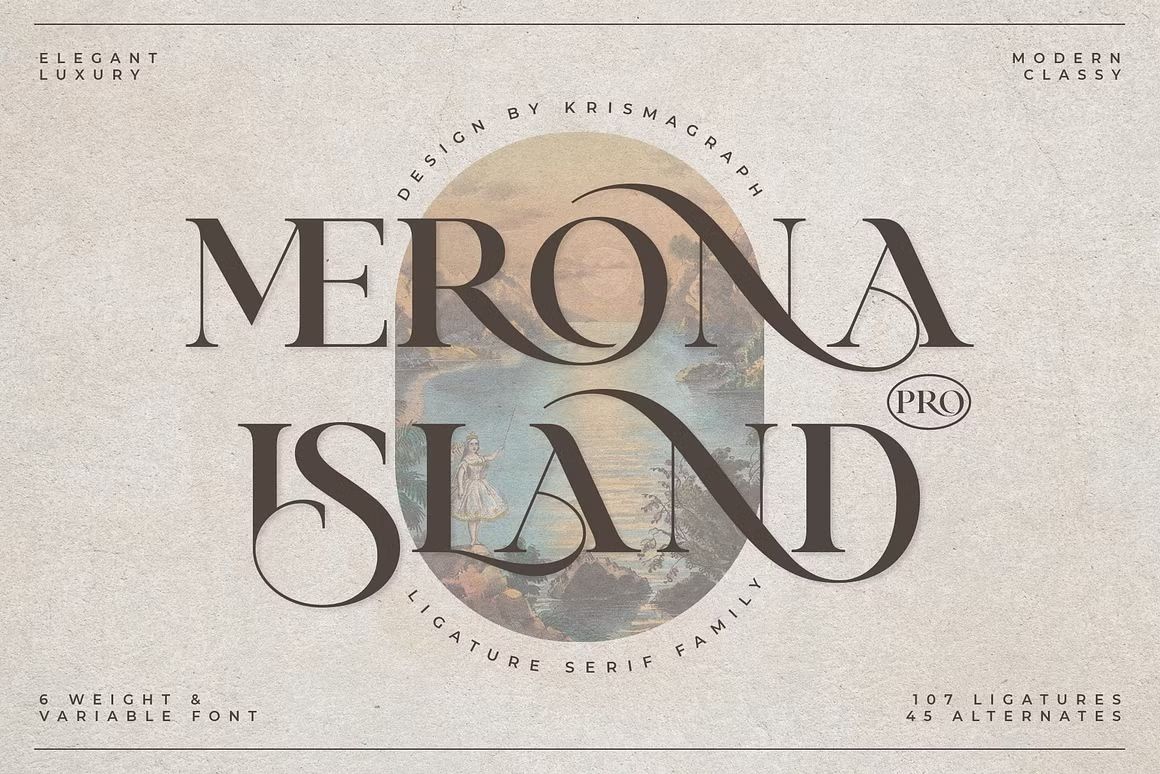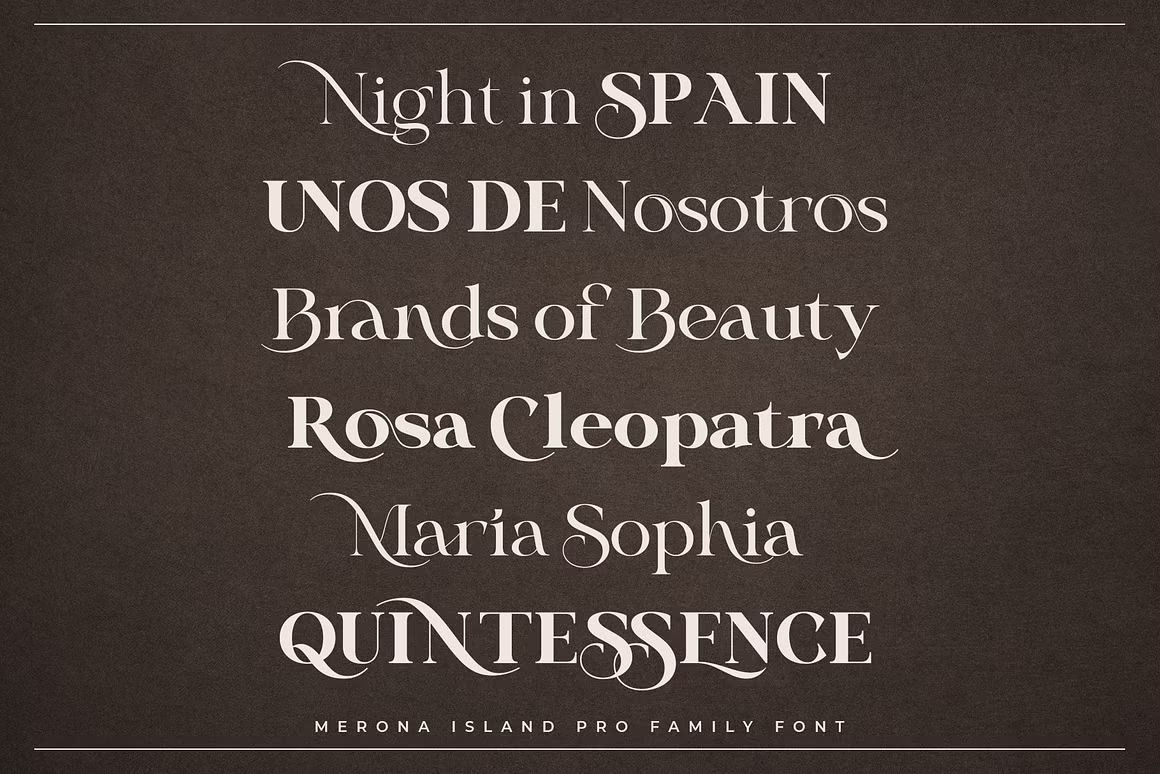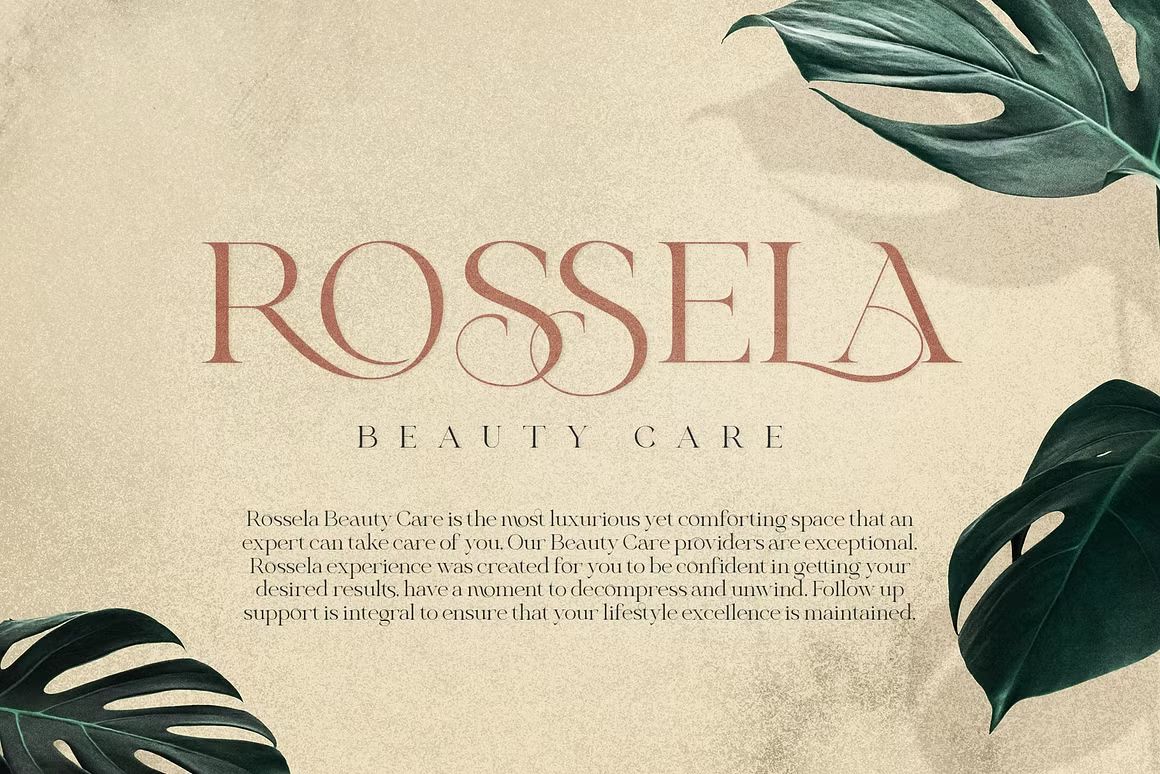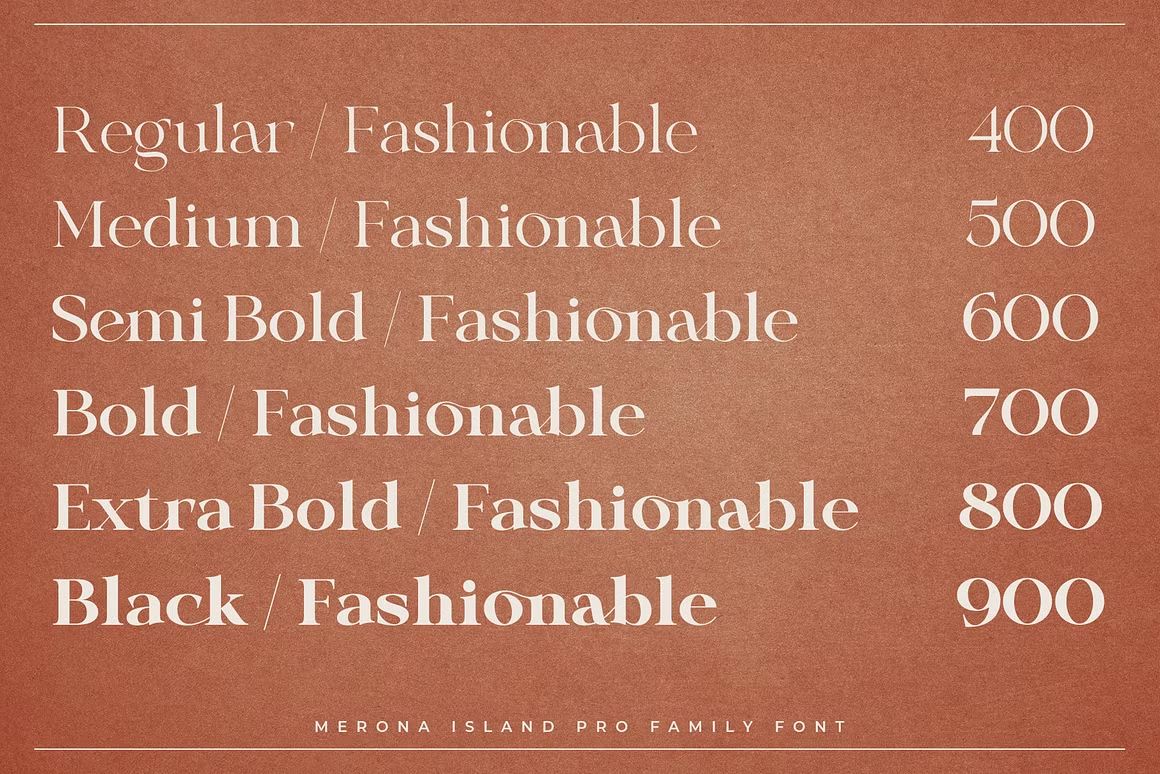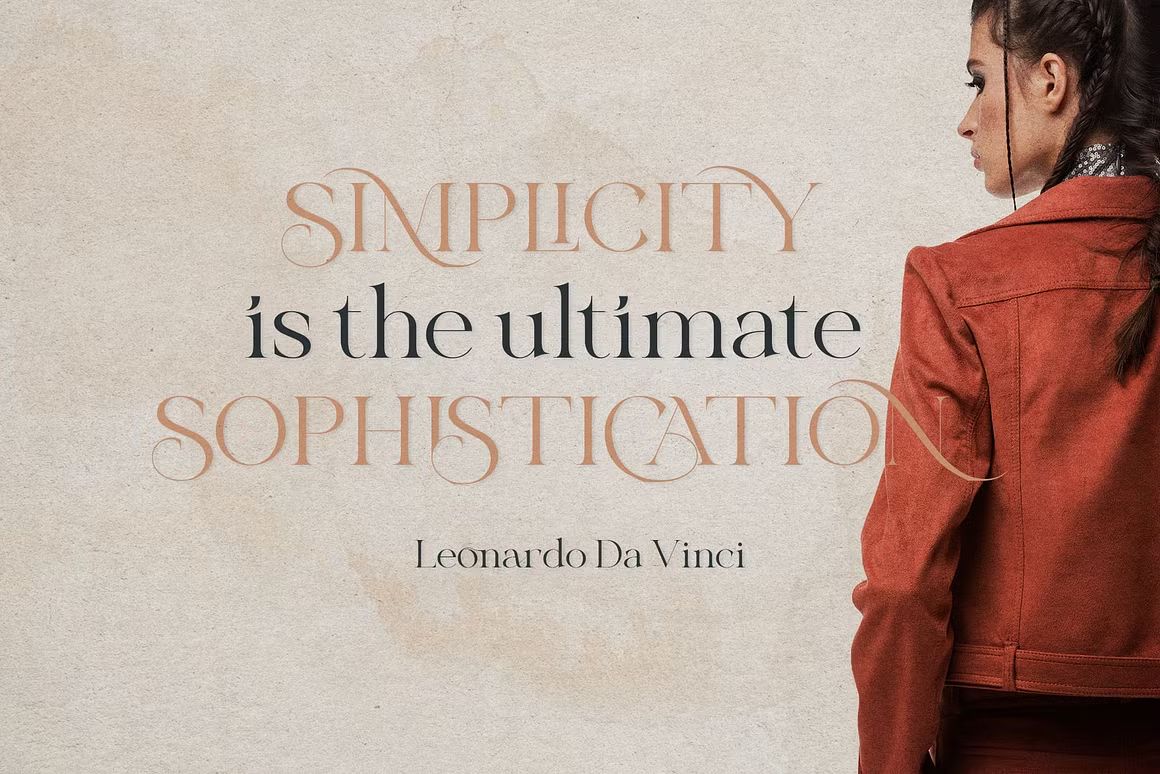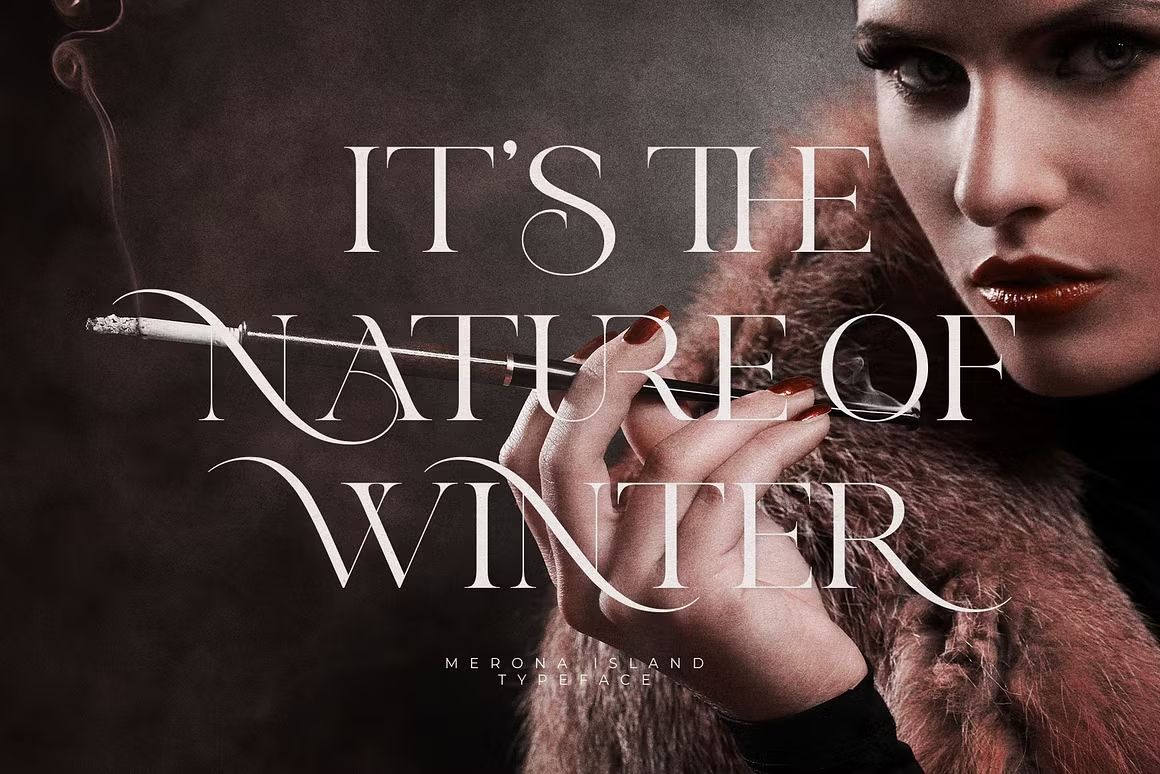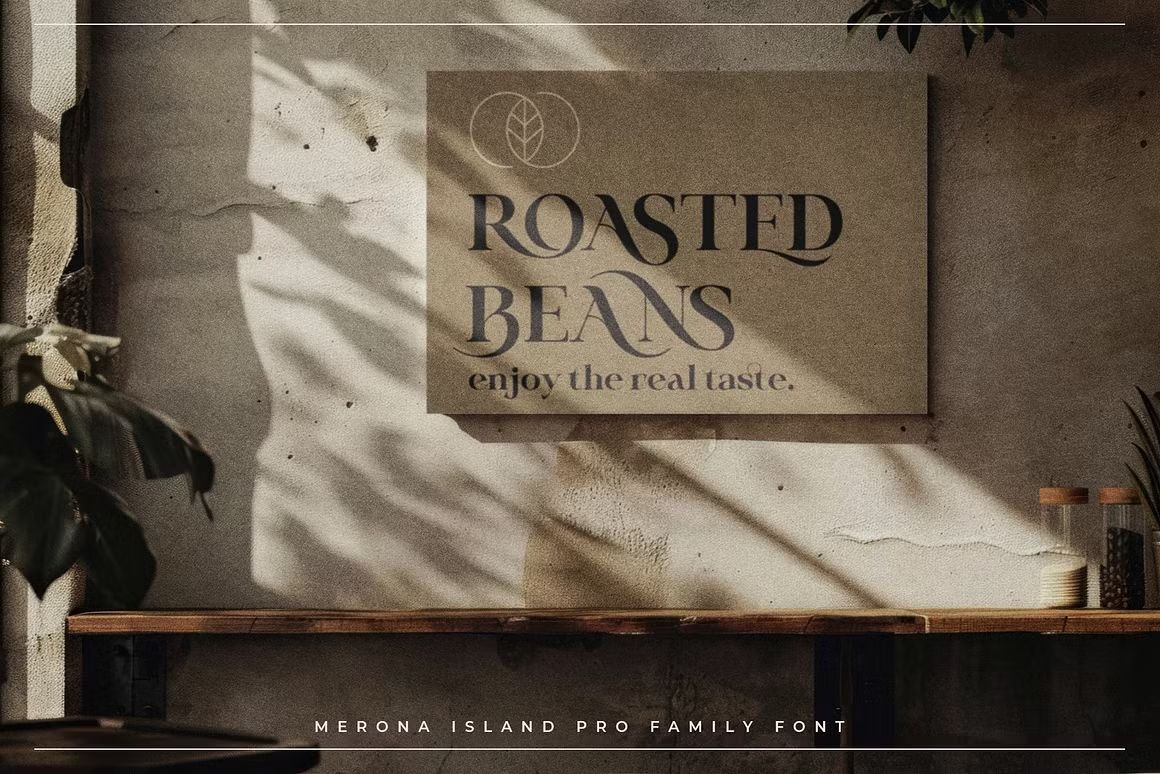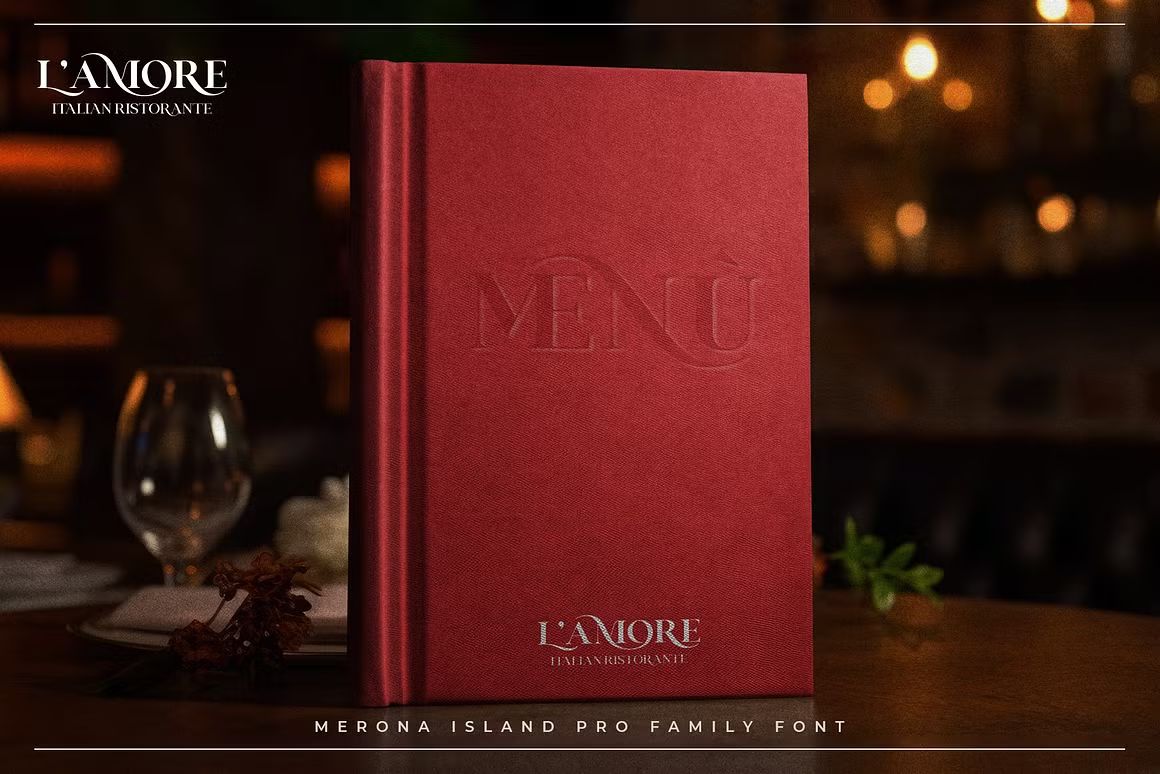
Merona Island PRO – Sans Serif Font
Merona Island PRO adalah font sans serif modern dan serbaguna, cocok untuk branding dan desain profesional. Tersedia dalam berbagai berat, format OTF/TTF/WOFF.
Merona Island PRO adalah font sans serif modern dengan tampilan bersih, geometris, dan profesional. Didesain untuk fleksibilitas tinggi, font ini cocok untuk branding, editorial, website, kemasan, dan desain korporat. Versi PRO ini dilengkapi dengan berbagai berat font, gaya alternatif, dan dukungan multibahasa yang membuatnya ideal untuk berbagai kebutuhan desain visual, dari minimalis hingga bold statement.
• Gaya sans serif modern & geometris
• Tersedia dalam beberapa berat (Light hingga Bold)
• Ideal untuk branding, UI/UX, dan desain cetak
• Dukungan multibahasa & karakter lengkap